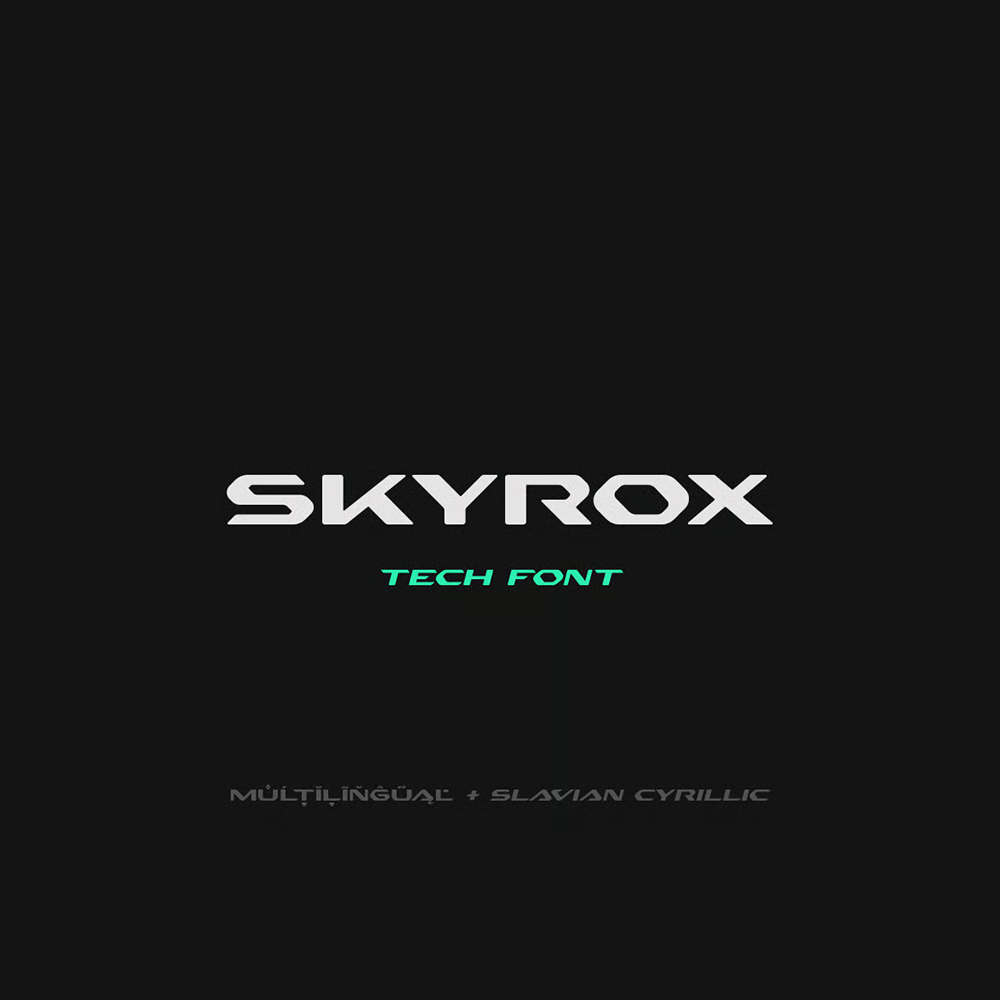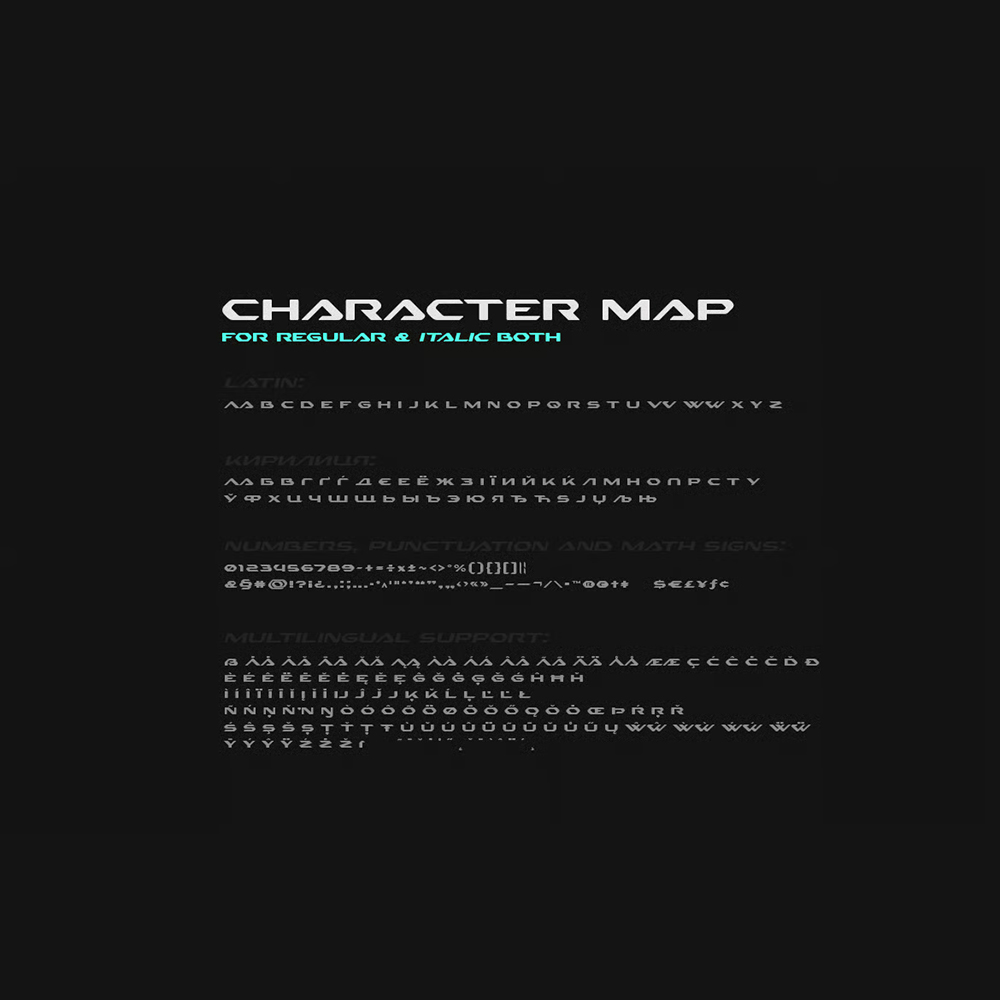
دانلود فونت انگلیسی Skyrox Font
فونت پرمیوم و انگلیسی Skyrox Font فضایی مدرن، آیندهنگر و با فناوری پیشرفته ایجاد میکند. Skyrox دارای دو نسخه ساده و ایتالیک میباشد که هم به عنوان سربرگ و هم به عنوان متن زیبا است. از آن در پروژههای خود در زمینههایی مانند رباتها و اندرویدها، فناوری پیشرفته، آینده، واقعیت مجازی، فضا، ورزش و بسیاری موارد دیگر استفاده کنید.